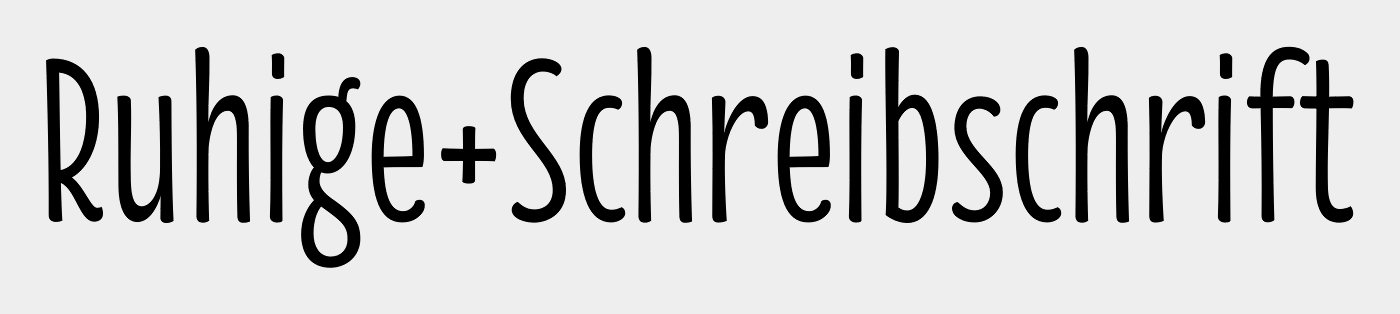
Suche ruhige Schreibschrift mit weichen Kurven
Hallo, ich suche für ein Logo mit dem Titel "Ruhepunkt" eine schöne Schreibschrift. Diese sollte weiche Kurven haben, vielleicht ganz ohne Kanten, lang gezogene Buchstaben und Ruhe ausstrahlen. Die Buchstaben sollten zusammenhängend sein. Ich weiss nicht genau wie ich es beschreiben soll. Bei linotype und myfonts bin ich leider nicht fündig geworden.
Weiss jemand vielleicht mit meiner Beschreibung was anzufangen und kann mir eine Schrift vorschlagen?
Da »zusammenhängende« Schreibschriften aber in der Regel von Natur aus dynamisch (also weniger ruhig) sind, würde ich eher auf eine Sans (vielleicht rounded, max. mit leichten handschriftlichen Einflüssen*) setzen.
Zum Beispiel Rubrik, Colette, Sauna oder
Florence
Vielleicht kennt aber auch jemand eine Schriftart ähnlich wie die von Sony Vaio, allerdings in zusammenhängenden Buchstaben und wie schon gesagt als Art Schreibschrift oder so ähnlich wie die Inkburrow in meinem Beispiel oben. Bei der Schriftart ist der Anfang sehr schön bis zum h aber der Rest ist dann wiederrum nicht ideal.
‘Zusammenhängend’ ist als Begriff für eine Schrift mit verbindende Schriftzeichen etwas verwirrend. Normalerweise wird der Begriff ‘zusammenhängend’ für den gestalterischen Zusammenhang bestimmter Schnitte, Zeichen, Striche bzw. Buchstabenteile benutzt. Wenn ich es zusammenfasse suchst du also eine Schrift die man normalerweise als breite, verbunden geschriebene aufrechte Schreibschrift bezeichnen würde? Die Striche des Sony Vaio logo sind linear, die der Inkburrow weisen einen höheren Strichstärkenkontrast auf, die der Mister K liegen dazwischen. Was entspricht deiner Meinung am meisten das wonach du suchst?
Hallo, sorry für die unklare Beschreibung. Genau wie beschrieben suche ich eine breite, verbunden geschriebene aufrechte Schreibschrift. Die Petras Script ist schon sehr gut. Vielleicht fällt einem noch eine alternative Schriftart ein. Ansonsten schon mal vielen Dank an alle.
ich werf gern nochmal die showcase von neulich in die runde (auch wenn die für meinen geschmack zu lieblich für den zweck ist)